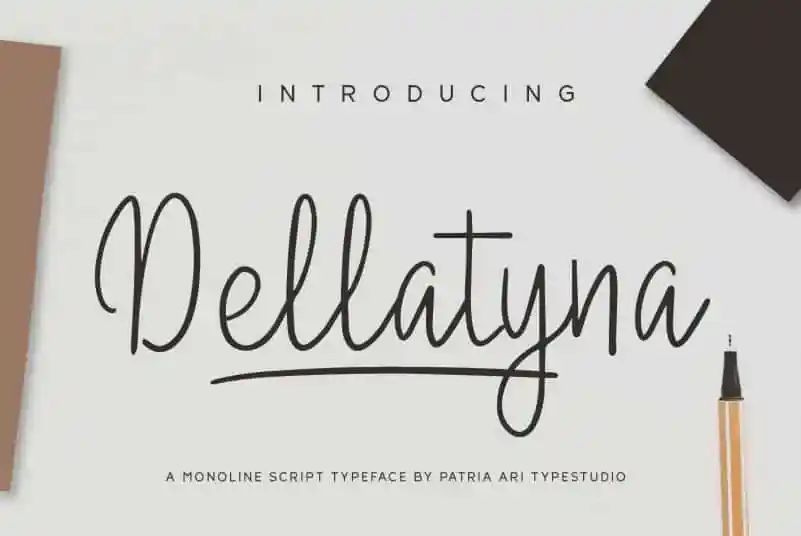
Dellatyna Handwritten Font – Download Grátis
A Dellatyna Handwritten Font é uma tipografia script monoline com sotaque multilíngue, além de swashes adicionais. Este tipo de letra é perfeito para aqueles que querem trazer um toque único e sofisticado a seus projetos. Seja você um designer gráfico ou criador de conteúdo digital, o Dellatyna é ideal para aplicar em diversas áreas, como capas de livros, materiais promocionais, cartazes, títulos, citações e muito mais. Com sua elegância natural e sutileza na escrita a mão, este fonte atinge uma paixão secreta pela arte do design gráfico. Se você procura um desafio para tornar seu trabalho ainda mais bonito e singular, o Dellatyna é definitivamente algo que vale testar.